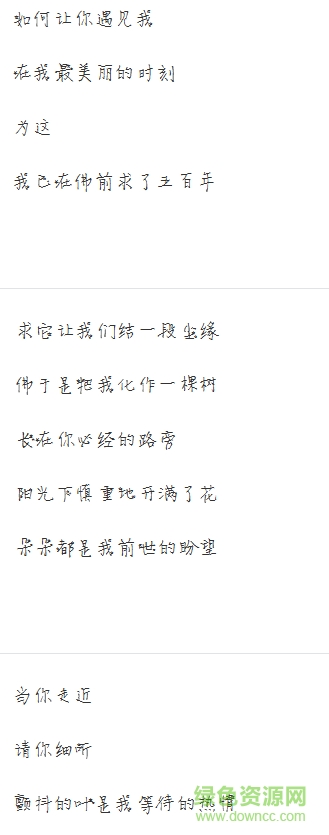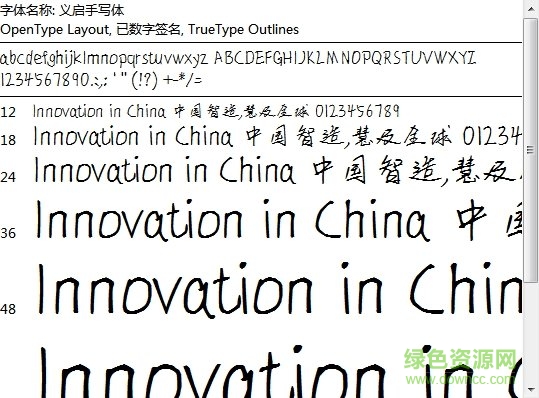
义启手写体ttf
义启手写体ttf是义启字库官方推出一款好看的钢笔四蹄,颇有瘦金体风格,字体美观大观,非常适合情书表白、诗歌写作等,需要的朋友请来绿色资源网下载吧!
字体介绍
义启字库以女孩笔迹为基础,融入天然、爽朗、以拙为巧等元素,设计出这款“义启手写体”。用笔洒脱自然,映带婉转但又不刻意雕饰。结构处理是以拙为巧的哲学理念,收处紧密稳如静子,放处疏简动如脱兔。章法是手写的灵魂,字与字笔断意连却自然天成。无故意为之但法度一体